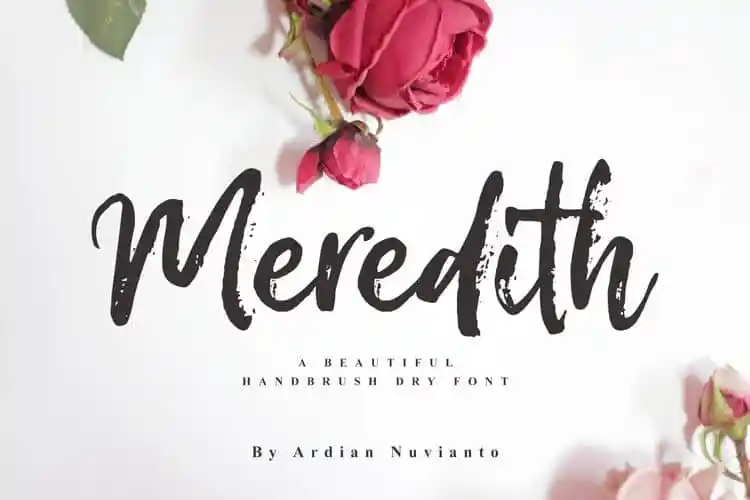
Meredith Brush Font – Download Grátis
A Meredith Brush Font foi criada pelo designer Ardian Nuvianto. Esta é uma fonte brush com movimentos naturais de raspar perfeitos para projetos incríveis. Suas linhas rústicas e áureas são ótimas para uso em produtos de beleza, capas de álbuns, revistas, capas de livros, embalagens de produto, banners ou embalagens de marca. Seu design perfeito combina com uma variedade de aplicações gráficas, desde criação de conteúdo de beleza até logotipos e materiais de comunicação. Sua simplicidade atraente torna-a ideal para adicionar um toque de personalização em qualquer projeto que você esteja desenvolvendo. Seja o seu próximo trabalho uma capa de produto inovadora ou simplesmente as embalagens da sua marca, Meredith Brush Font se destaca como fonte brush perfeita para designers e criadores de conteúdo. Engane-se se acha que a Meredith Brush Font é apenas um design de rascunho: ela será uma escolha ótima para qualquer projeto que você esteja trabalhando.